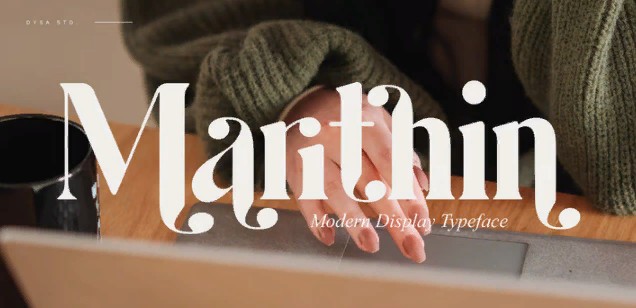
[Myfonts] Marithin Font (2021)
Название: Marithin Font (2021)
Marithin - это новый современный шрифт.
Эта очередная коллекция шрифтов Serif идеально подходит для вашего следующего проекта брендинга, отлично подходит для вашего бизнеса.
Marithin имеет гладкие края, поэтому этот шрифт создает ощущение подлинной ручной работы.